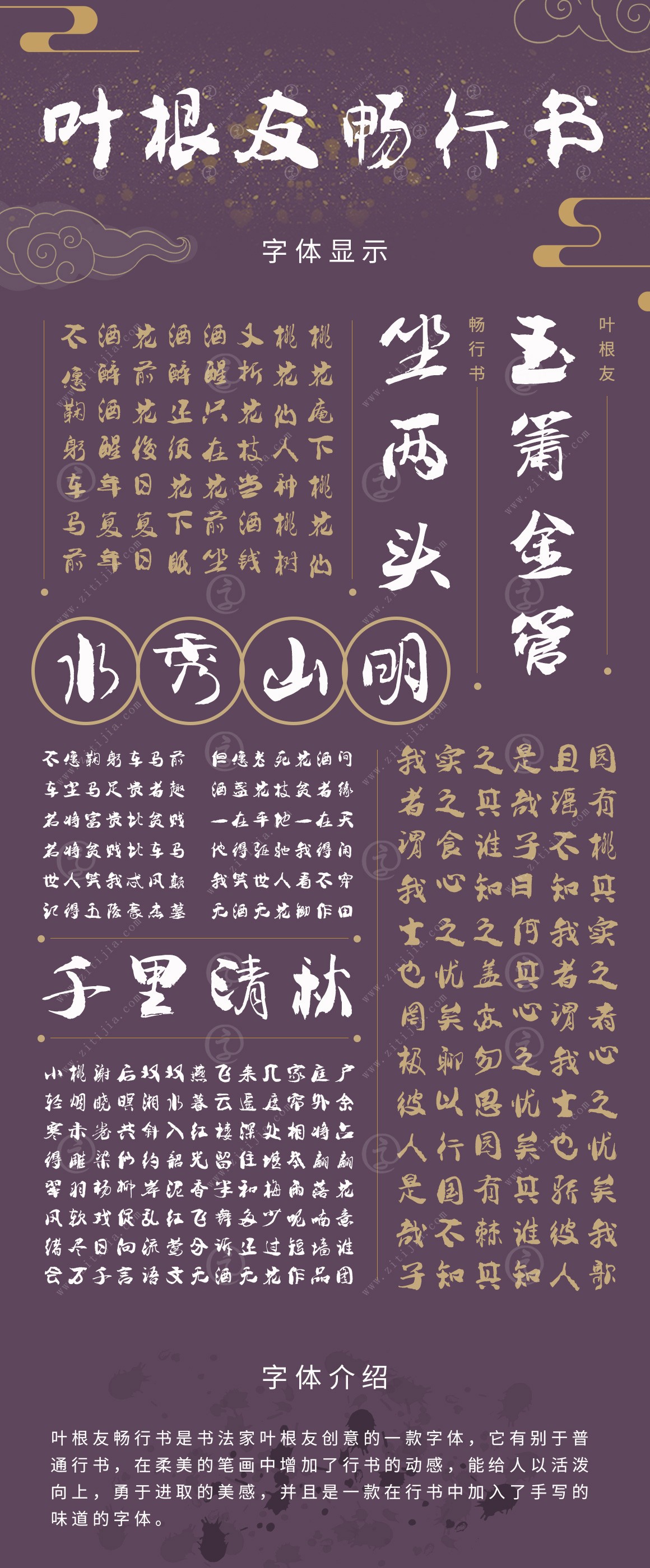
葉根友暢行書(shū)
字體作者:葉根友
創(chuàng)作年代:2015年
字體字?jǐn)?shù):6763個(gè)中文漢字以及其他英文字母和阿拉伯?dāng)?shù)字
字體介紹
葉根友暢行書(shū)是一款2015年最新創(chuàng)作的行書(shū)字體,這款字體是葉根友行書(shū)繁的簡(jiǎn)體風(fēng)格版本,從2008年到2015年,歷時(shí)七年的變化和書(shū)法風(fēng)格路線的創(chuàng)新,葉根友的書(shū)風(fēng)也引起了一定的變化,在字面上,書(shū)寫(xiě)的更加流暢和筆勢(shì)上筆走龍蛇之輕車(chē)駕馭,在標(biāo)題應(yīng)用、廣告標(biāo)語(yǔ)等不錯(cuò)的應(yīng)用選擇。